明日即将迎来一年一度的六一儿童节,这一天孩子们可以尽情享受欢乐。看到小孩子们天真无邪的笑脸,散发着阳光开朗的气息,总让人不禁想乘坐时光机器回到儿时那个无忧无虑的纯真的童年时光。 下面的卡通字体字体图片生动活泼, 跳跃明快, 节奏感和韵律感都很强, 也给人一种生机盎然的感受,在设计中传达出的效果极佳。
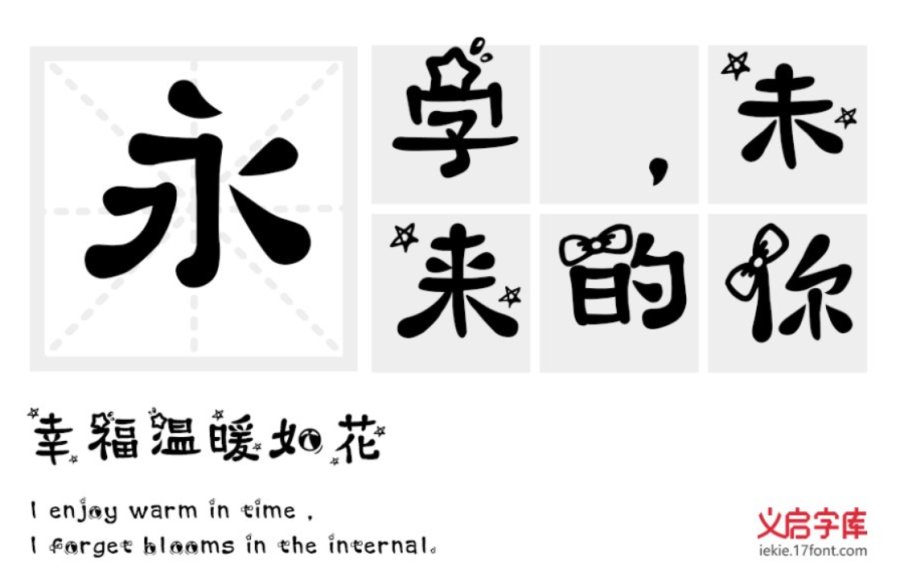
熊孩子体:有乖孩子也有“熊孩子”,胡搅蛮缠没规矩,调皮可爱搞破坏的“熊孩子”。这款字体加入了星星、蝴蝶结、水滴等元素,使得字体栩栩如生,像拿着发卡蹦蹦跳跳捣乱的“熊孩子”似的,充满生机。造型独特,不同一般灵动新颖。
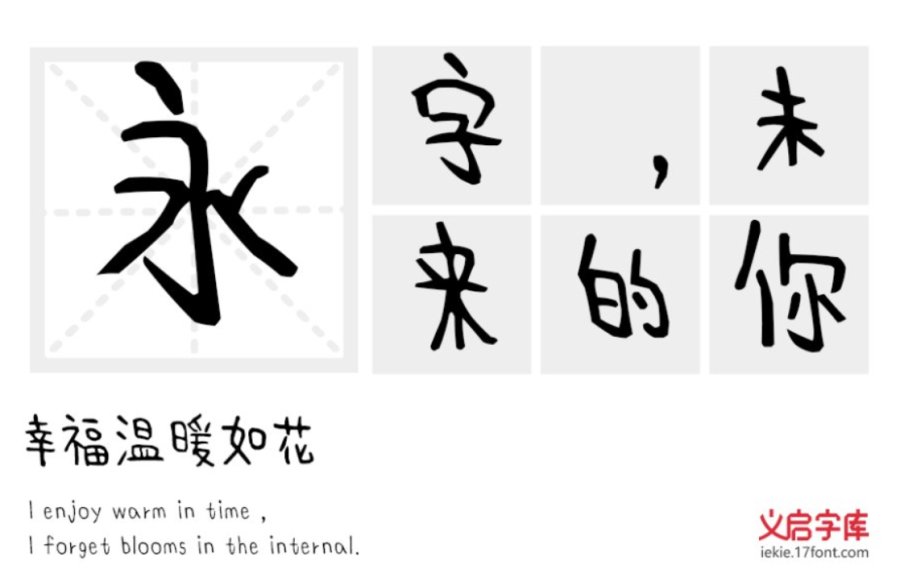
义启童趣体:这款字体以儿童的手写体构成,运笔粗细一致、字形稚嫩童真,折角处尖锐。结字充满卡通意味,妙趣横生。
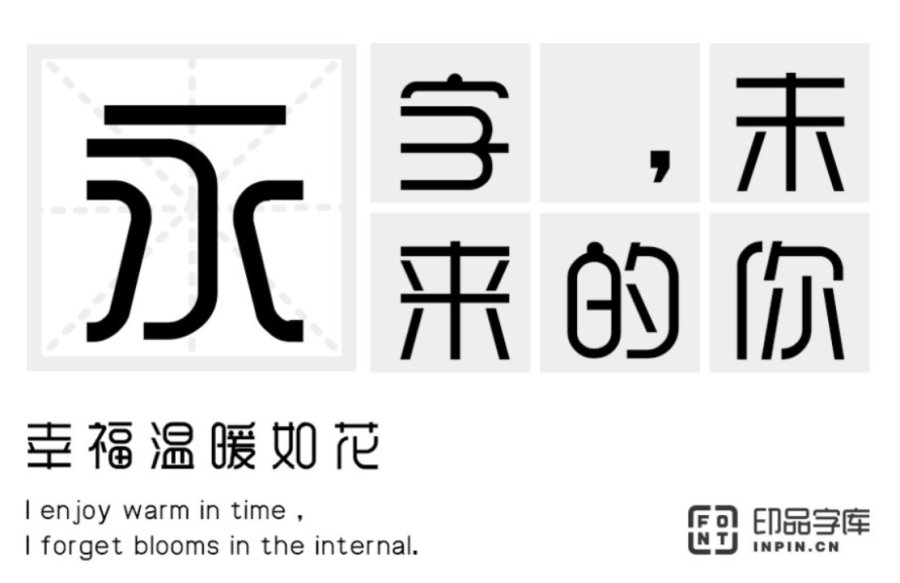
印品雅圆体:这款字体对弧形做了内凹外凸的处理,使得笔画更加居中圆滑。表面结构匀称统一,字型做了细致比例的调整,整体观来更加珠圆玉润。加强装饰感的同时,多添了一分俏皮可爱。